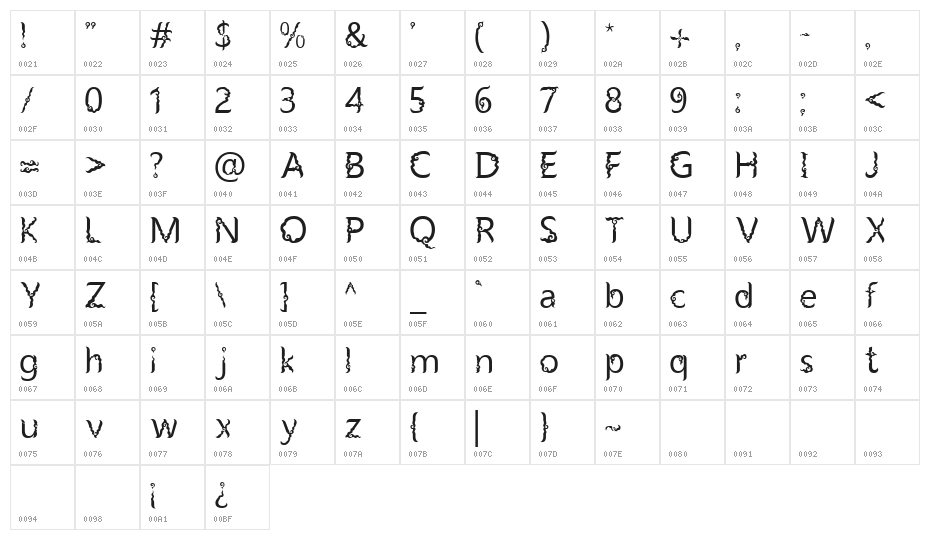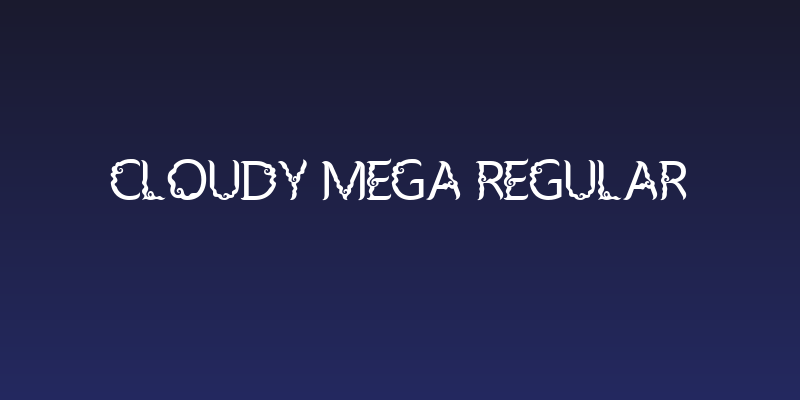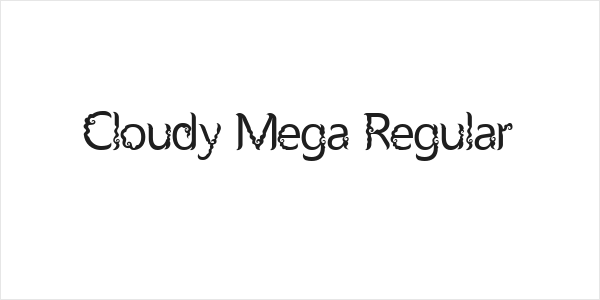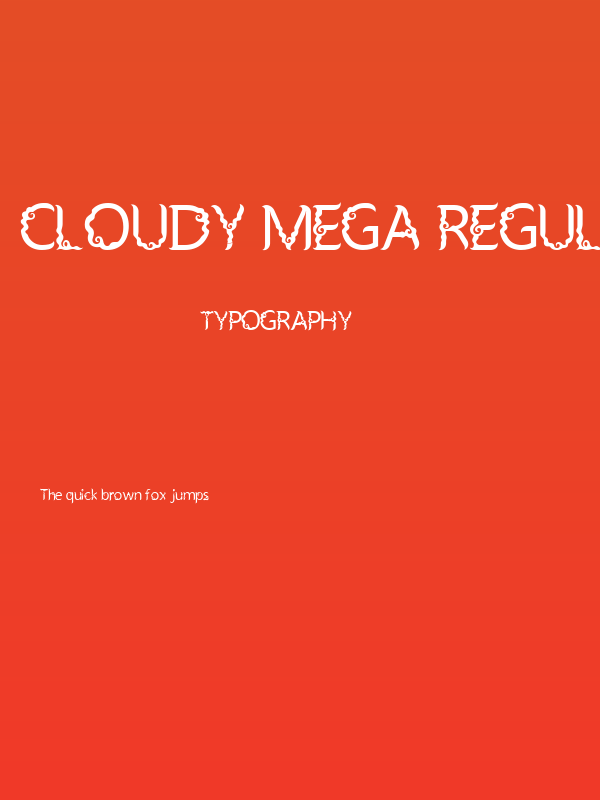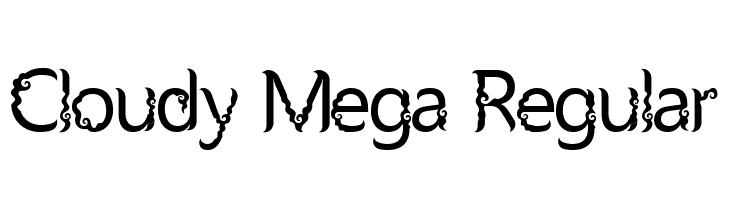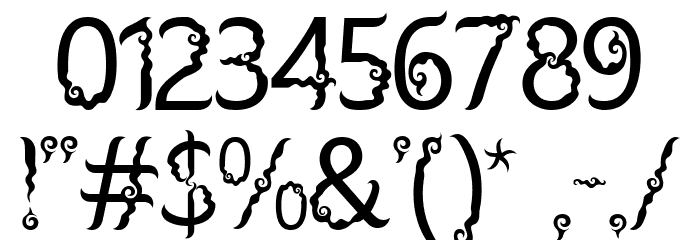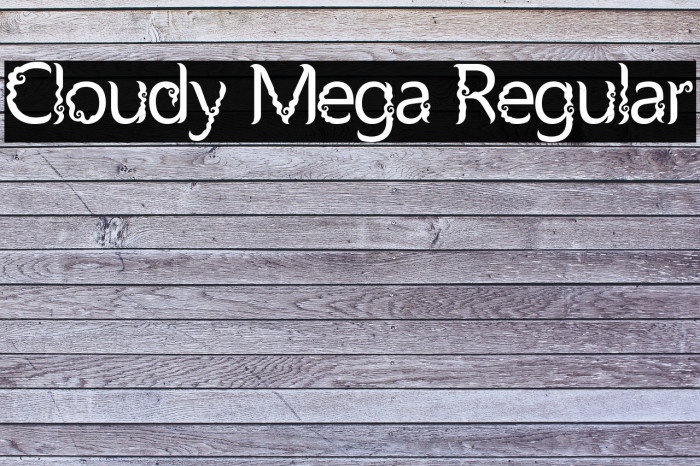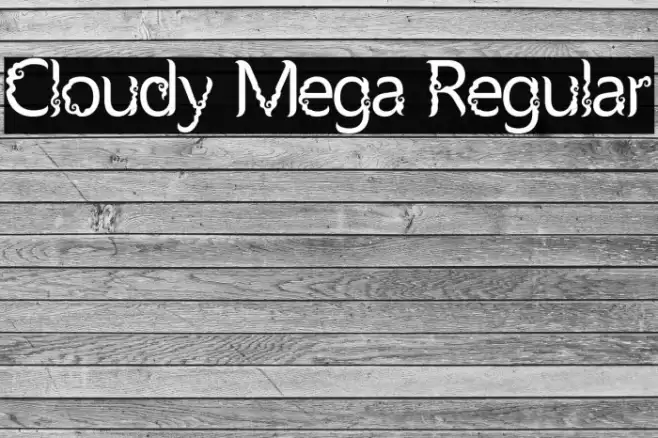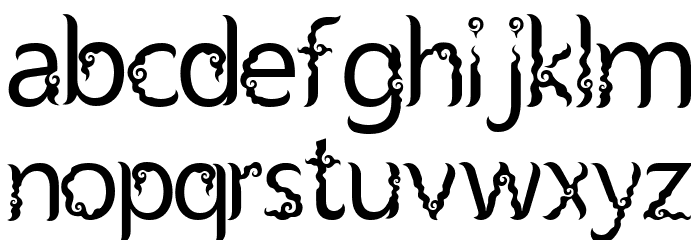
Cloudy Mega Regular Font
| Caso d'uso | Headlines, Logos, Artistic projects |
| Progetti proposti | Ideal for invitations, greeting cards, posters, and branding that require a playful and artistic touch. |